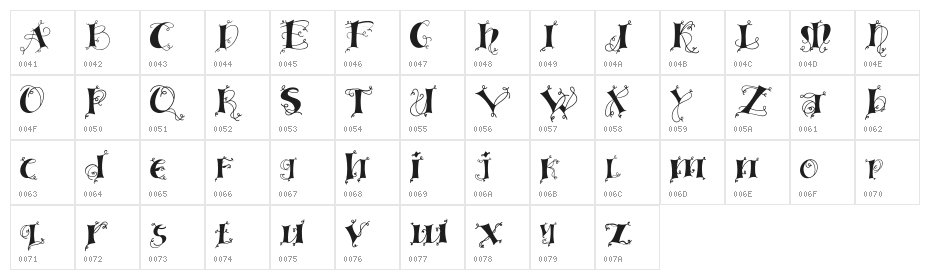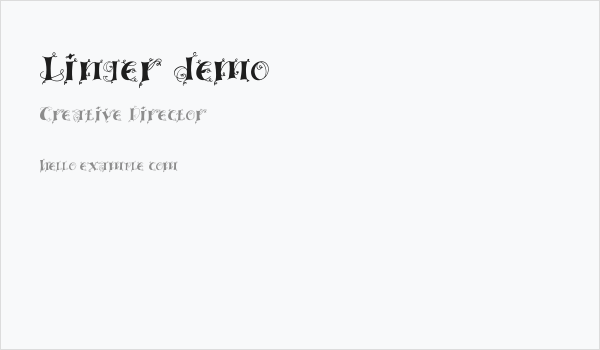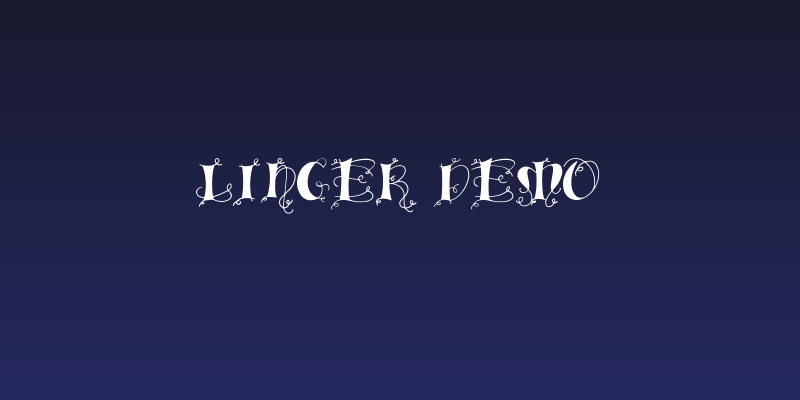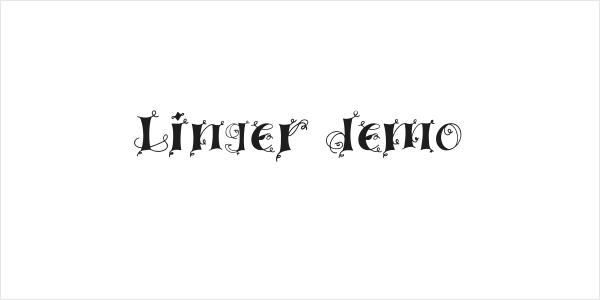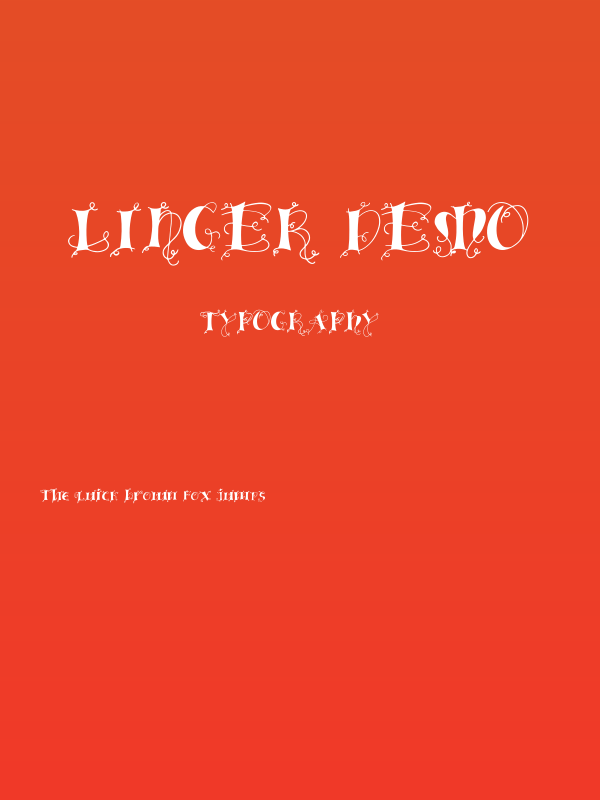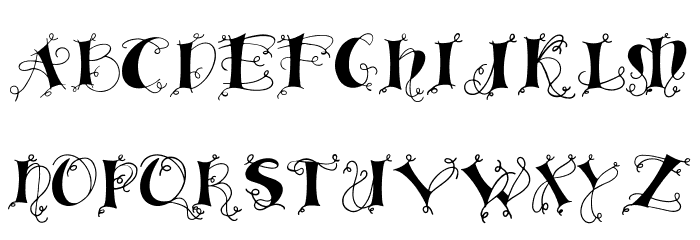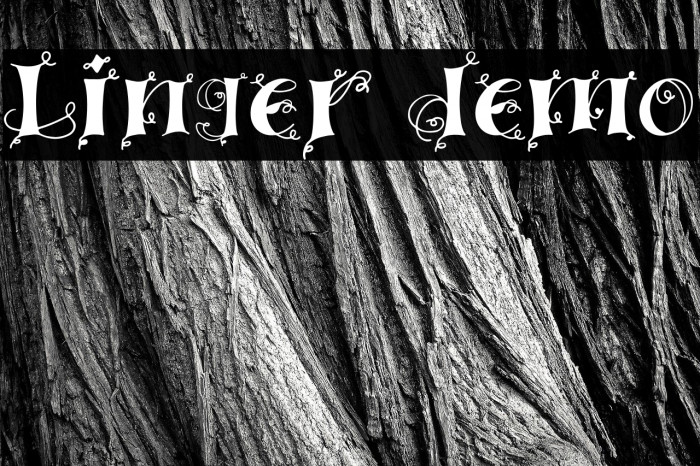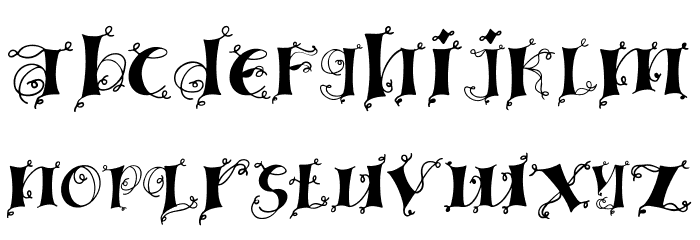
Linger demo Font
✎ Decorative
| Caso de uso | Logos, Invitations, Artistic Projects |
| Proyectos propuestos | Perfect for wedding invitations, greeting cards, artistic posters, and branding projects that require a creative and elegant touch. |